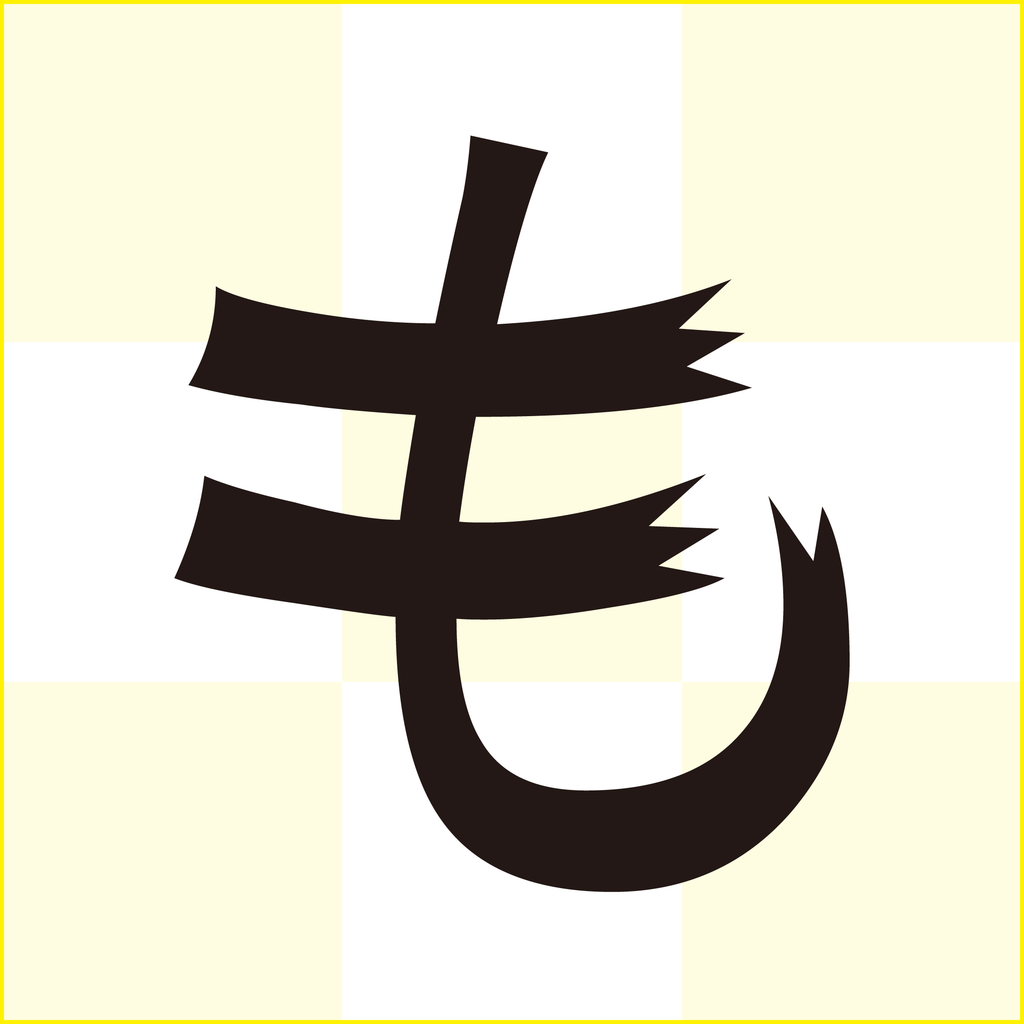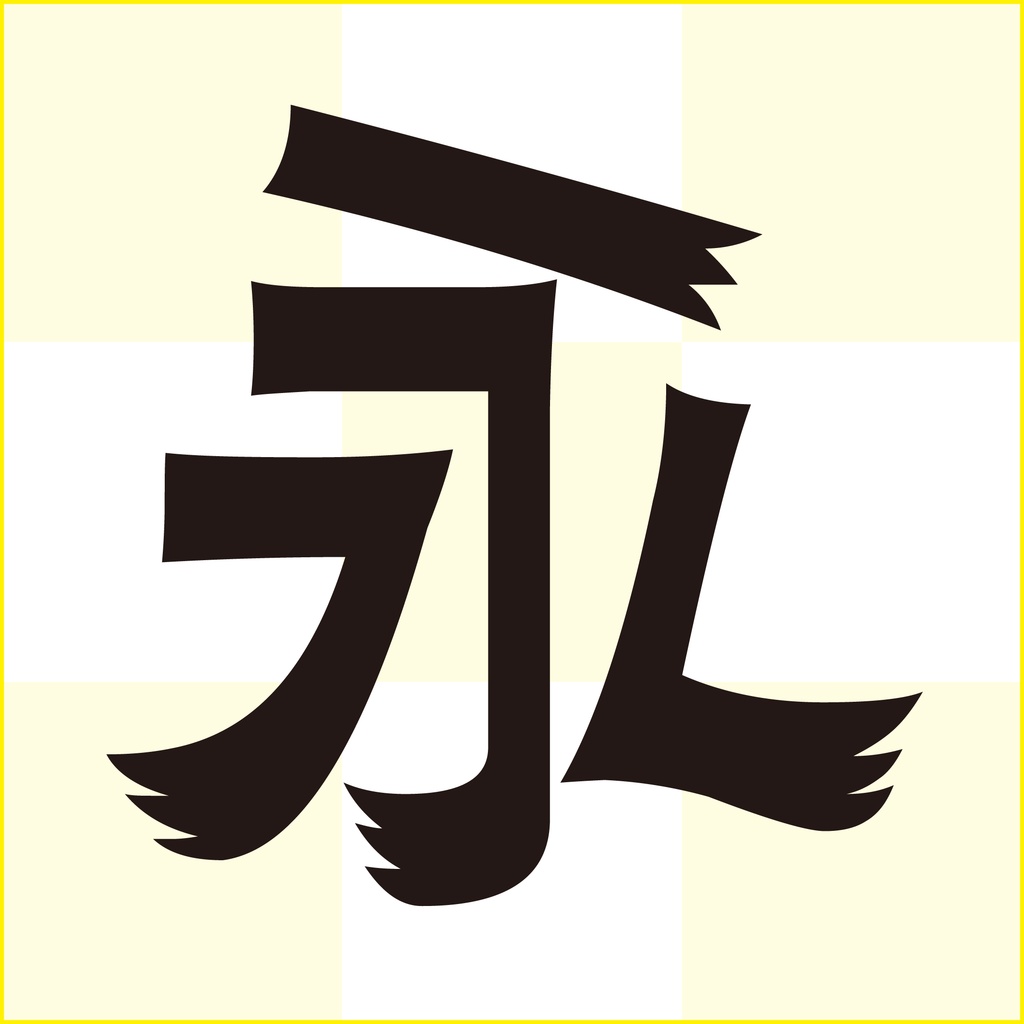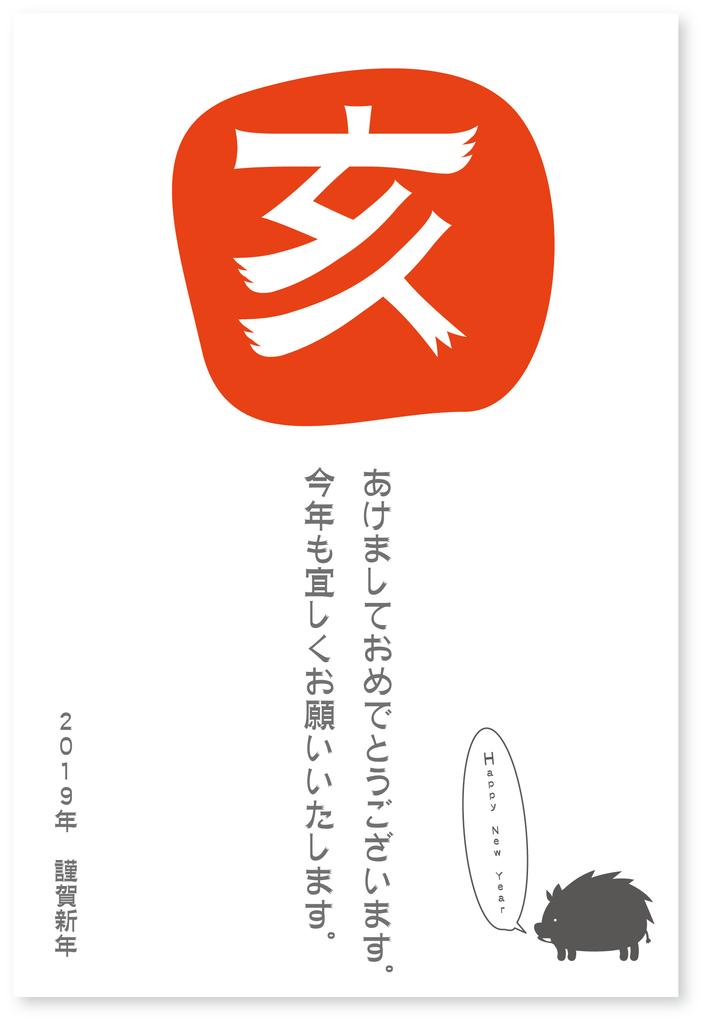
漆風隷書体
中国清代の画家である金農による独特な漆書からインスピレーションを得て作られた書体。金農の漆書は、楷書と隷書の力強さがあり、太い横画と細い縦画、角張った転折が特長で、漆風隷書体は金農の書風をベースにし、収筆部分にかすれたようなデザインを施すことで、現代的な解釈の新しい隷書体になっている。
漆風隷書体 文字見本(W7)